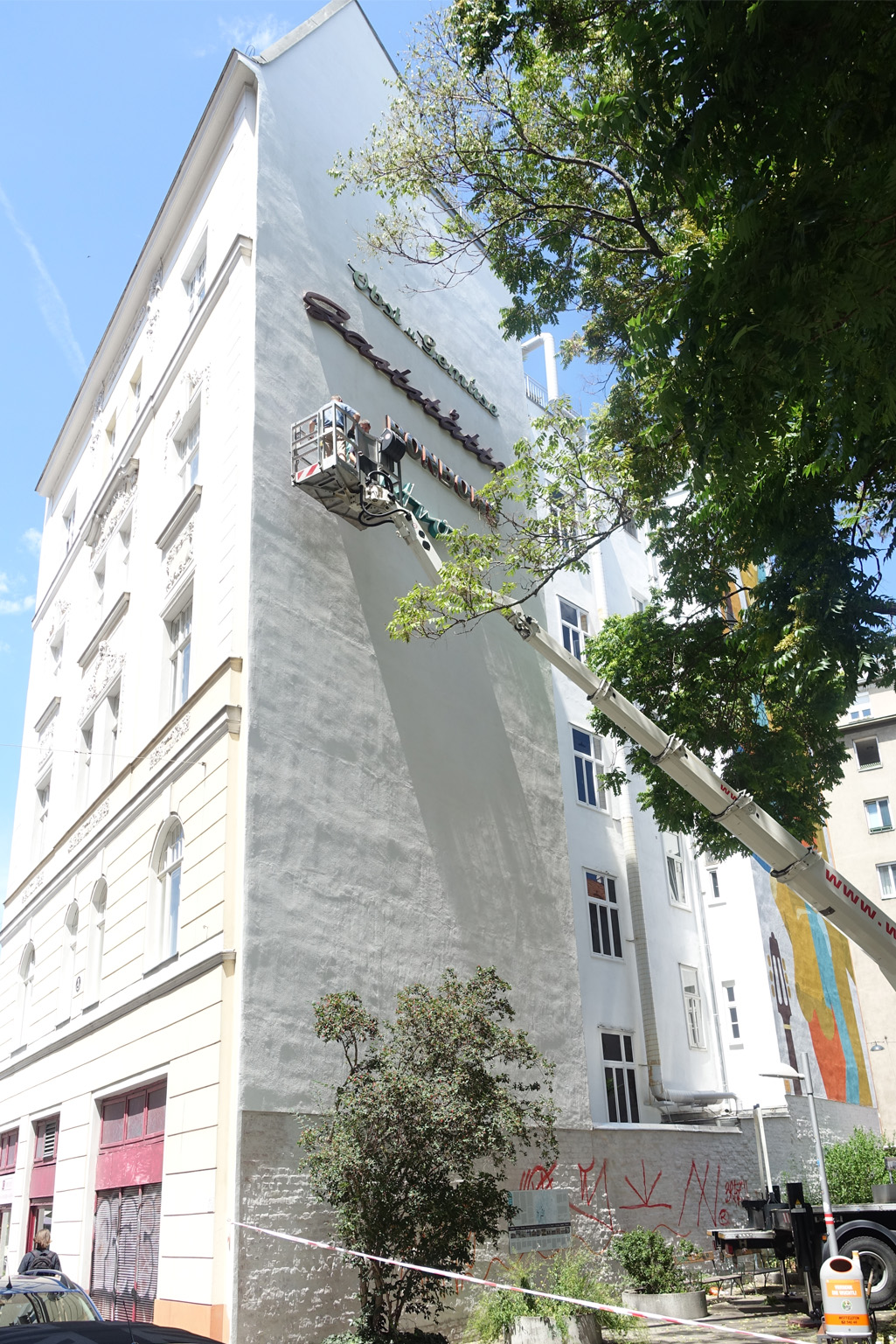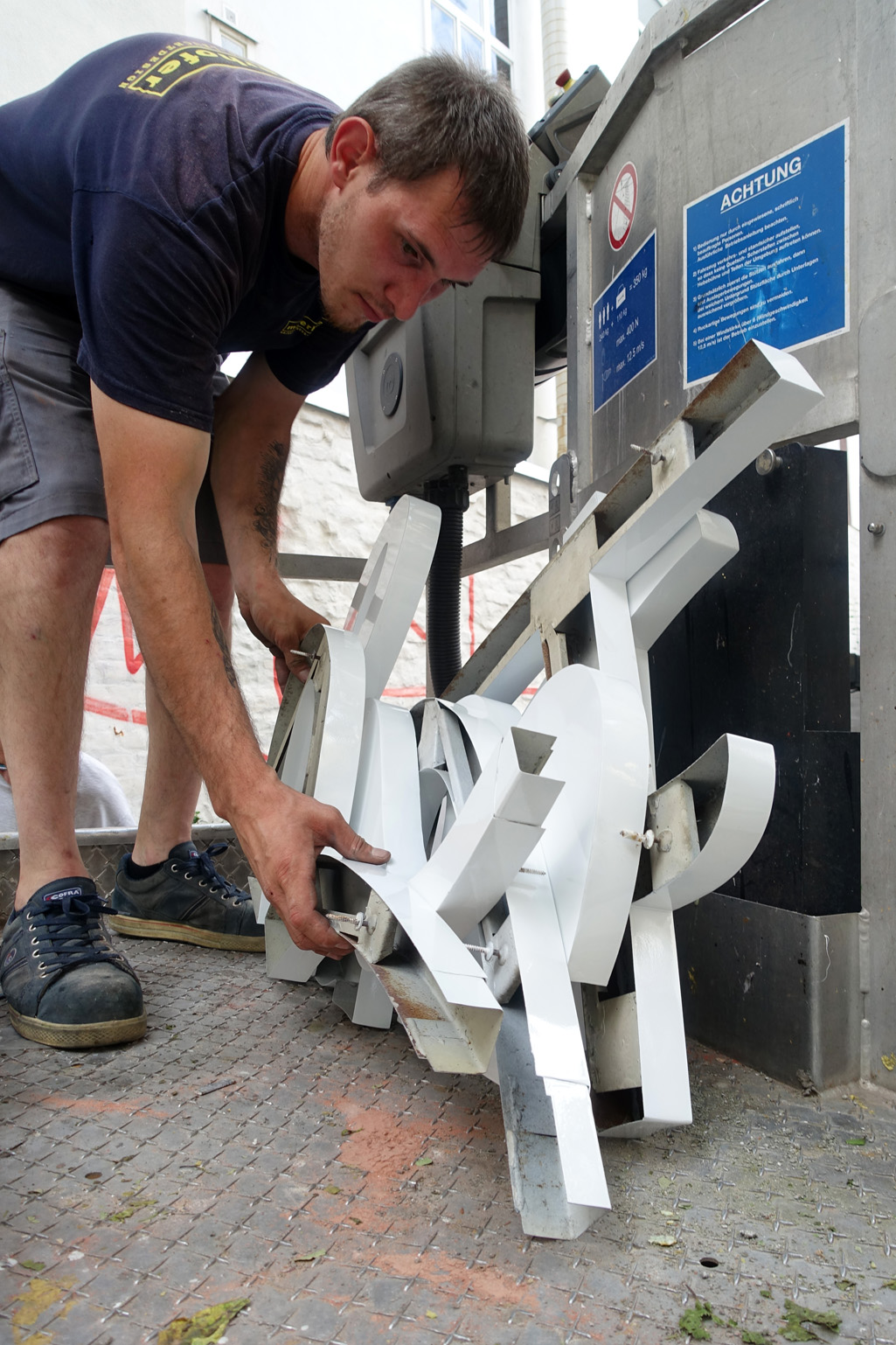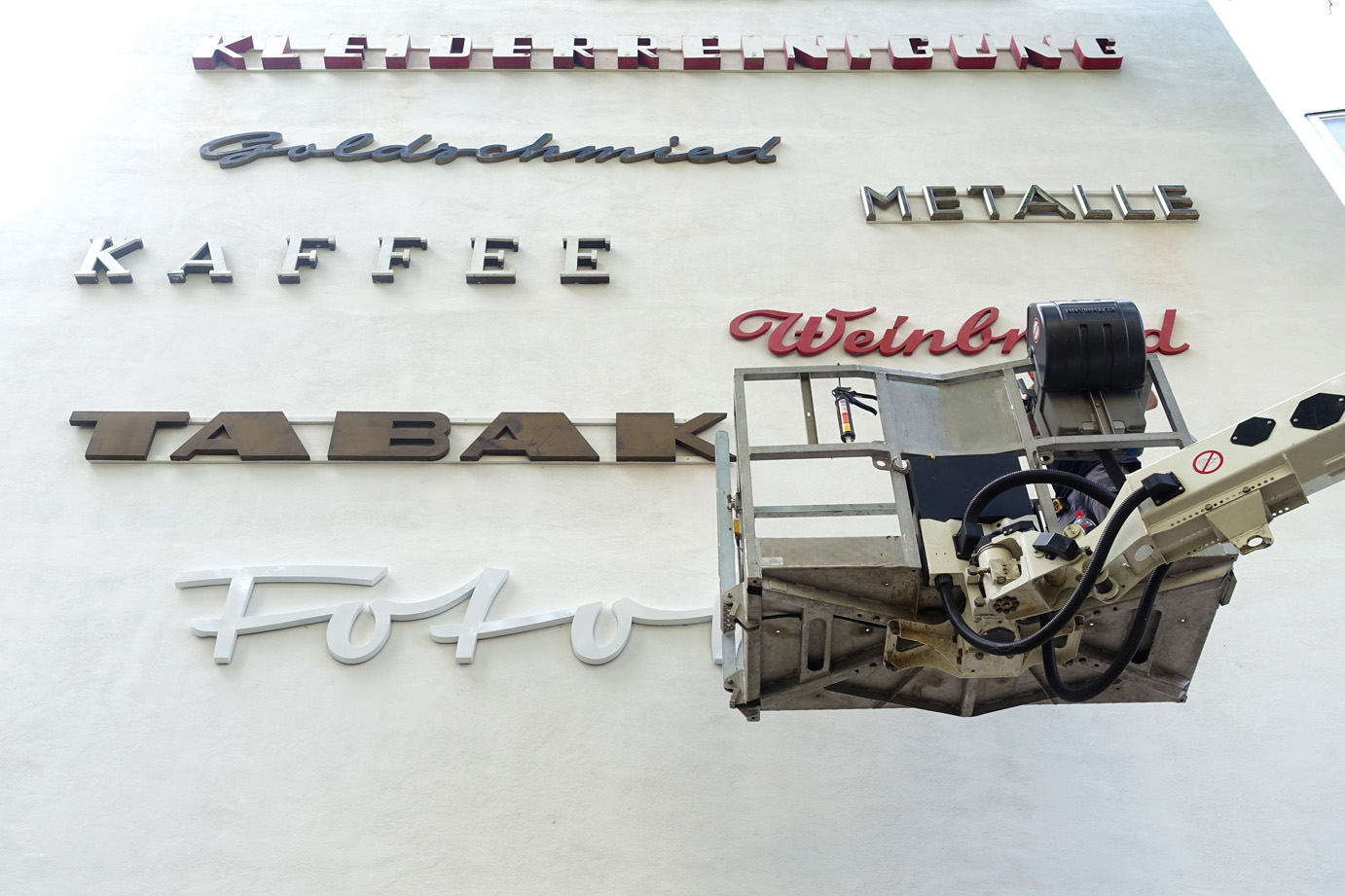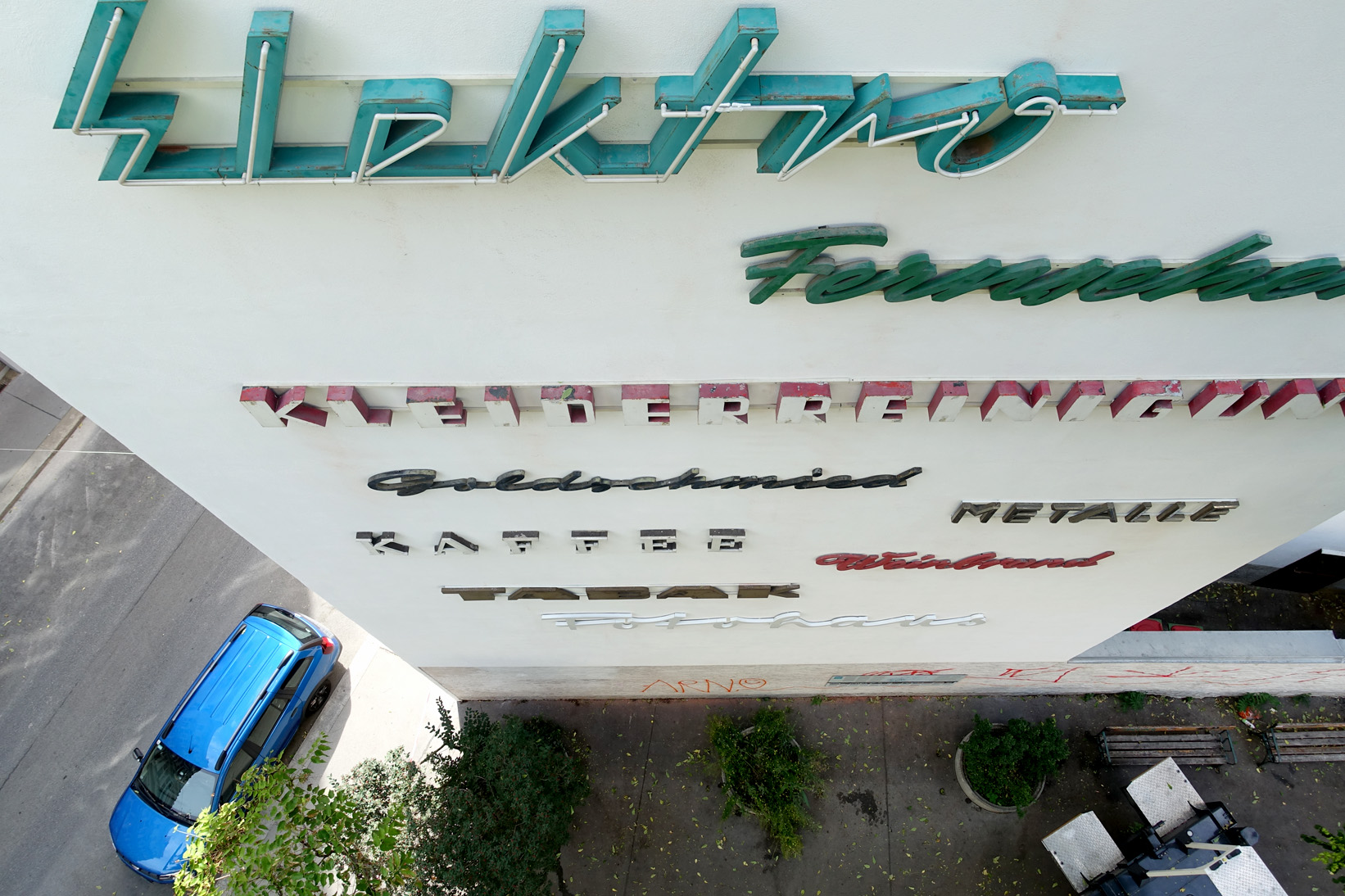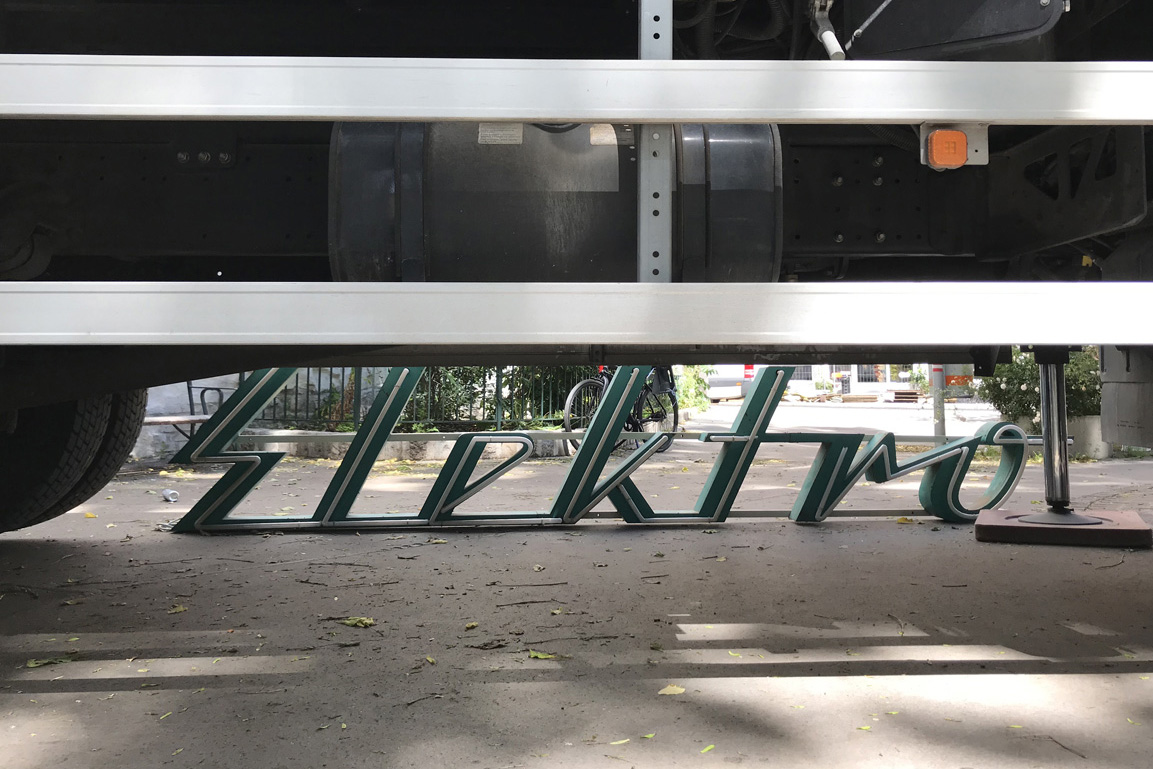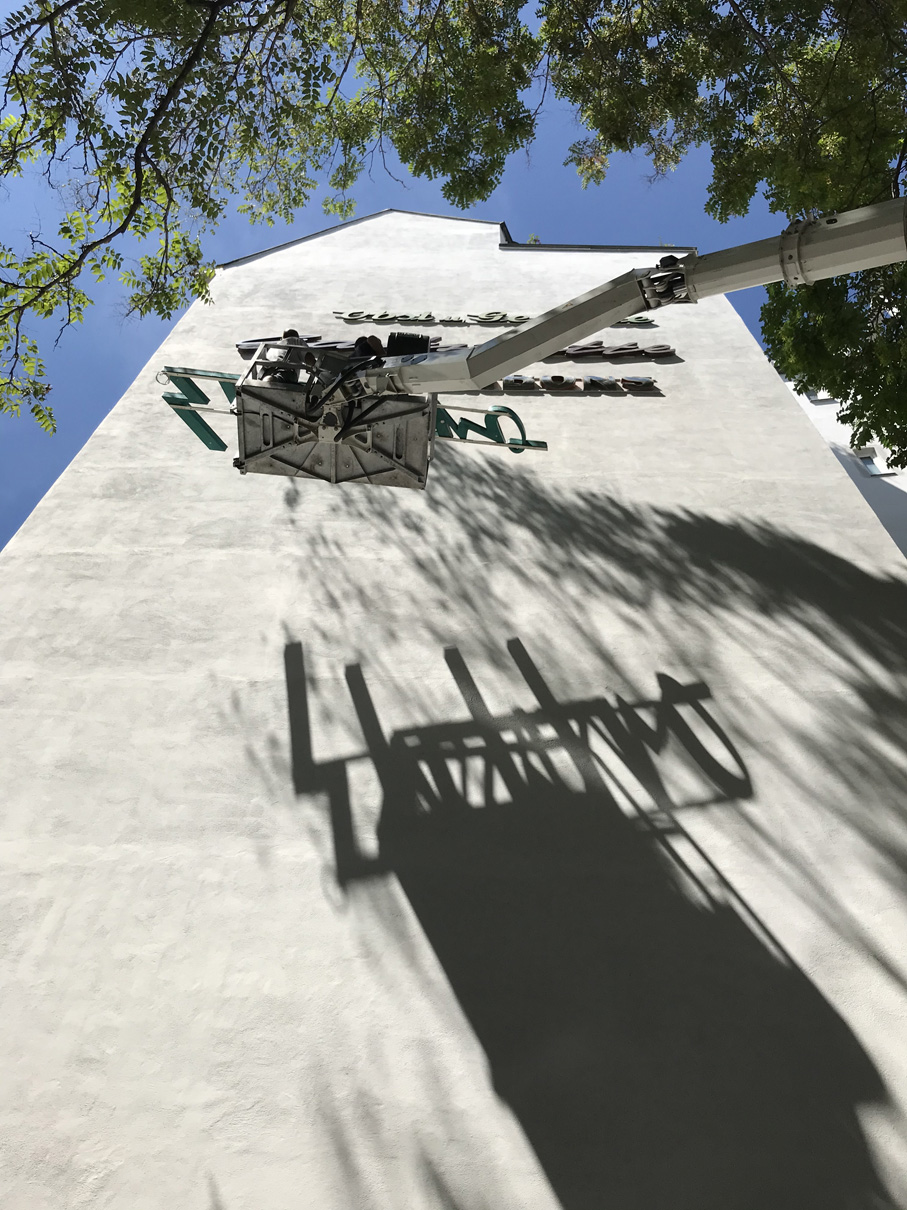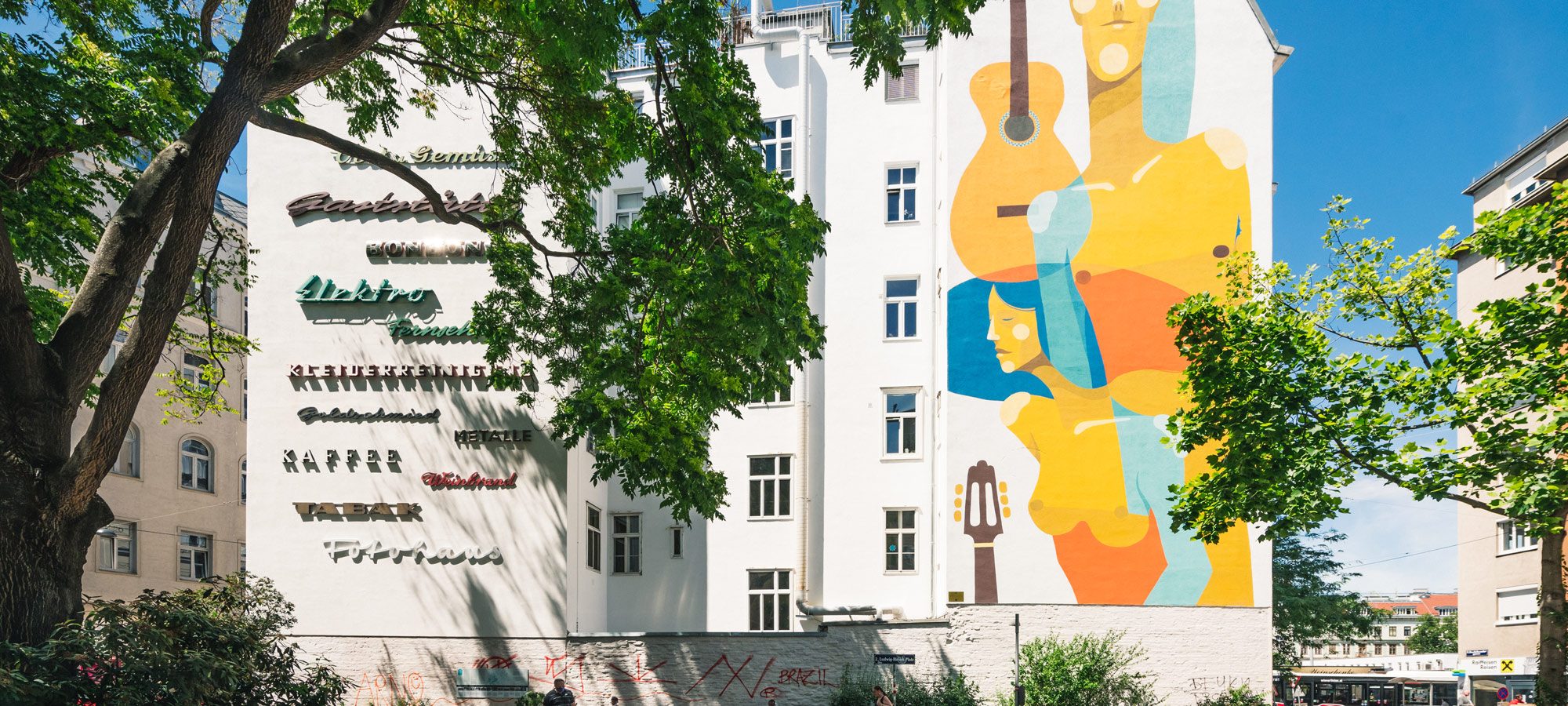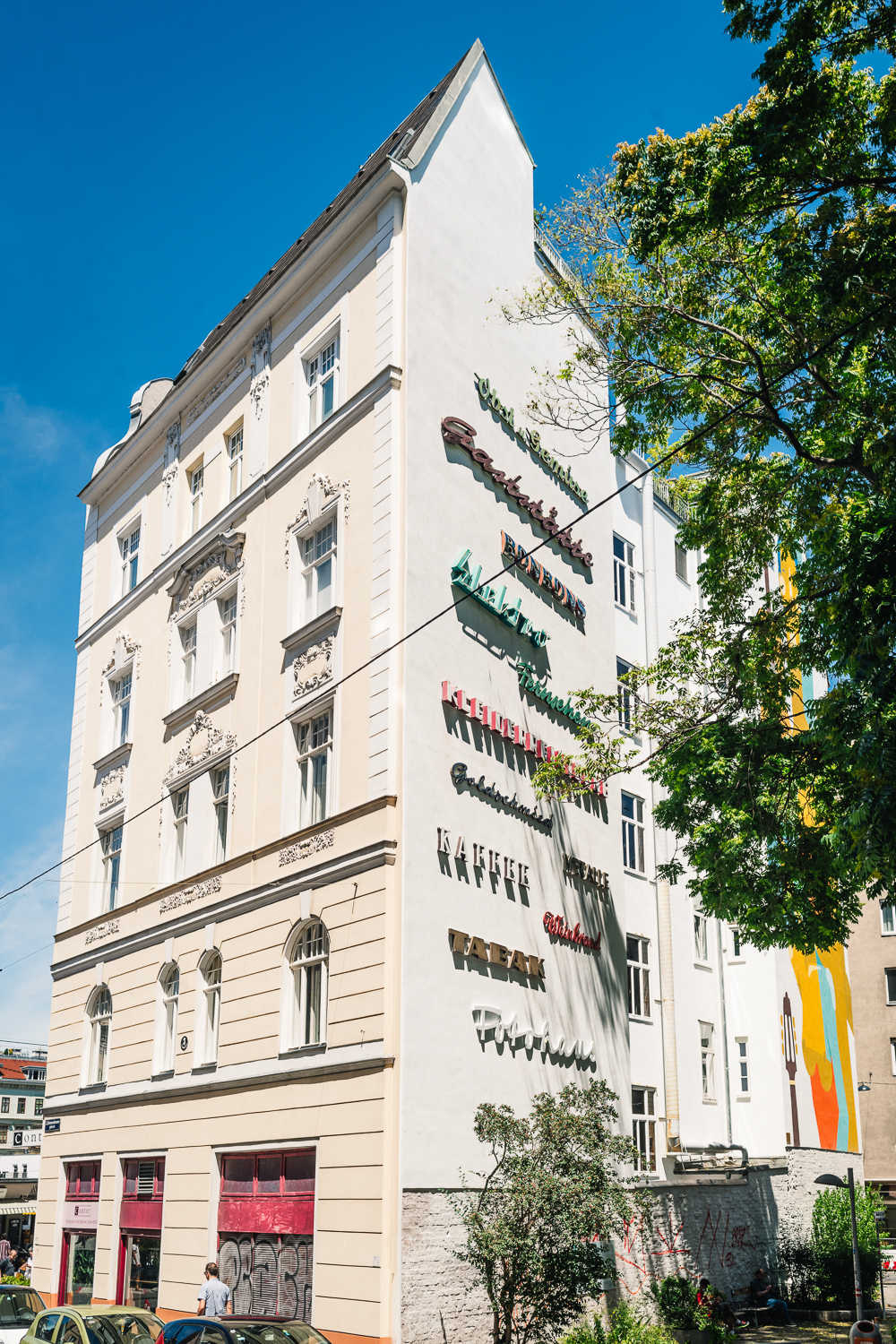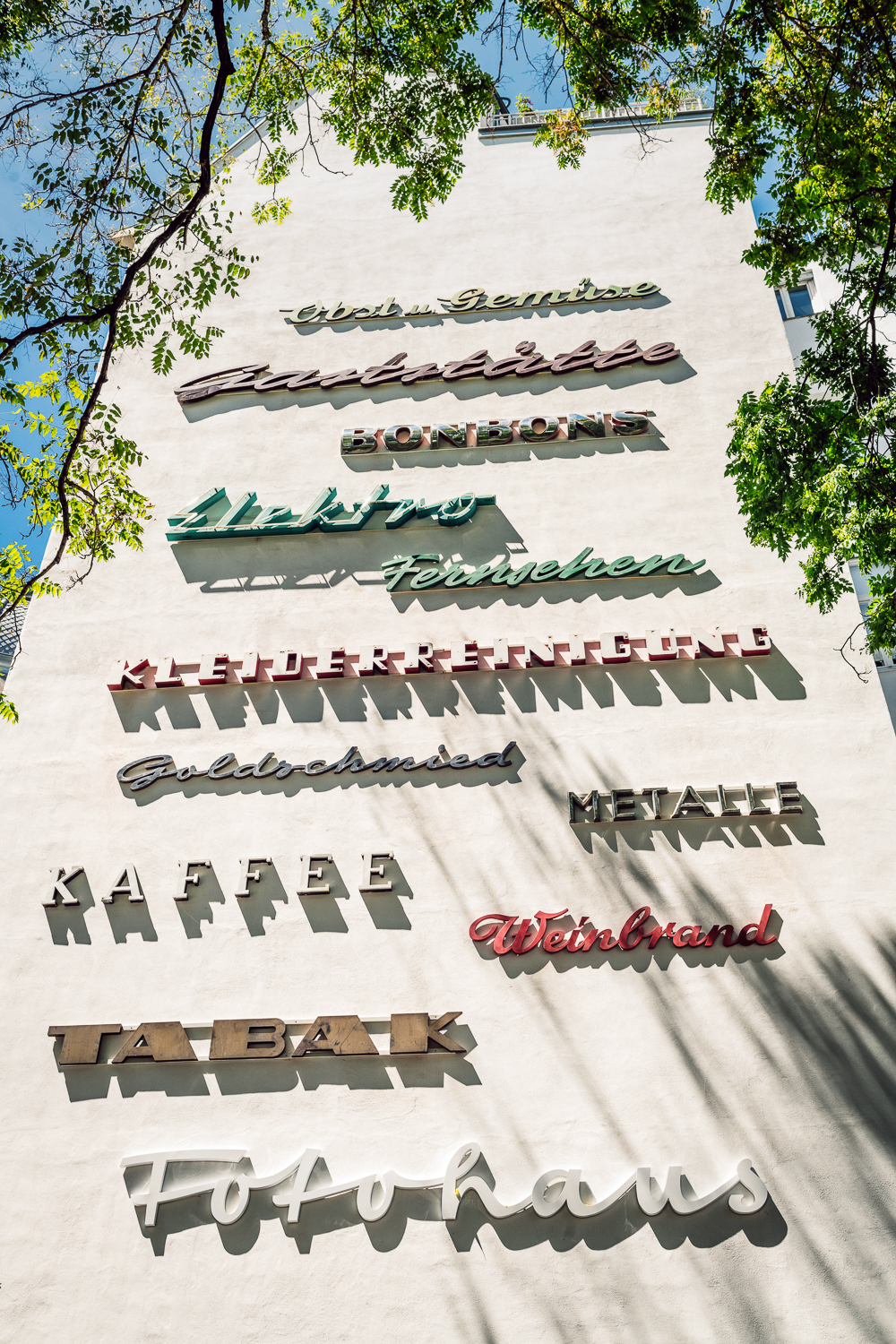
Mauerschau 1020 Ludwig-Hirsch-Platz
Ludwig-Hirsch-Platz, 1020 Wien
Vier Jahre lang war unsere erste Ausstellung historischer Wiener Fassadenbeschriftungen in der Kleinen Sperlgasse zu sehen. Zum Baubeginn der Sperlgymnasium-Erweiterung mussten wir die Schriftzüge im September 2018 demontieren.